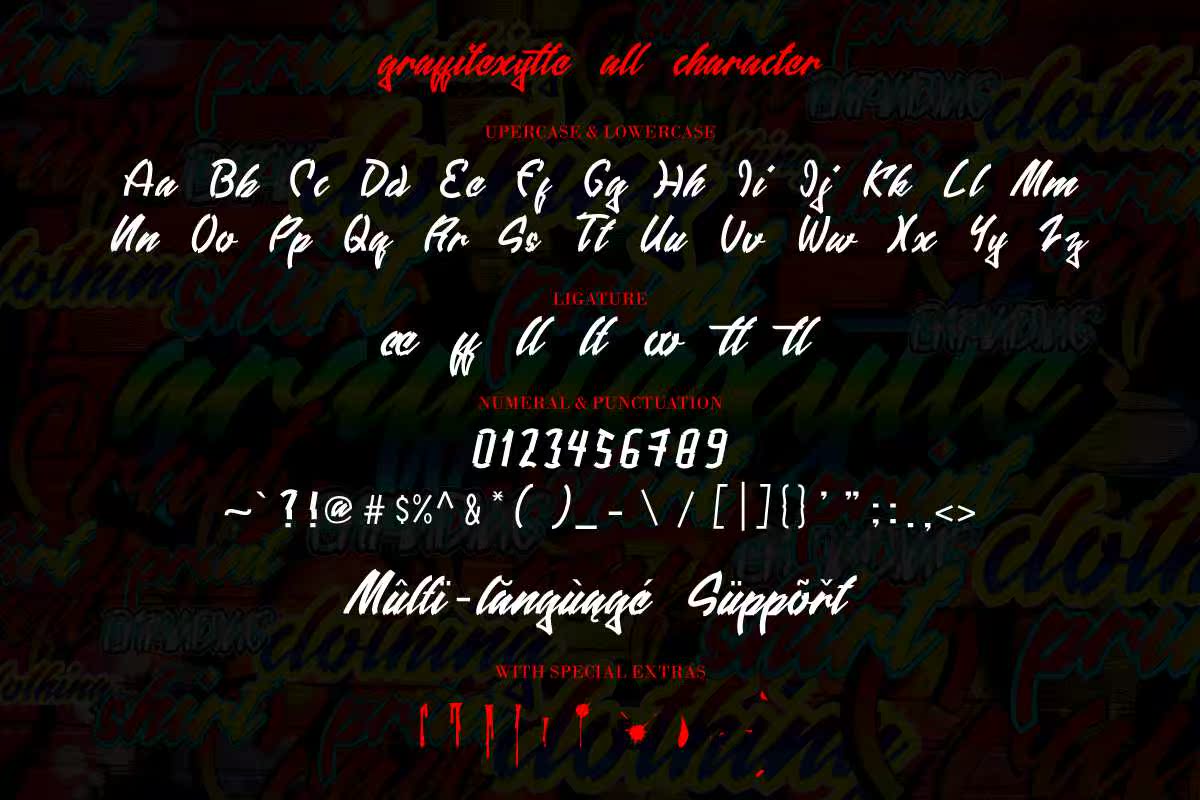
涂鸦风格是一种具有LockScriptStyle风格的涂鸦风格。它的灵感来源于具有较高艺术价值的网络写作。涂鸦风格适合于制作讣告标题,也适用于添加独特且引人注目的印刷设计,如T恤、贴纸、传单、,很快,涂鸦就成为了一种具有锁定脚本风格的游戏。它受到了具有较高艺术价值的网络写作的启发。涂鸦不仅适用于讣告标题,也适用于添加独特且引人注目的印刷设计,如衬衫、贴纸、传单等。